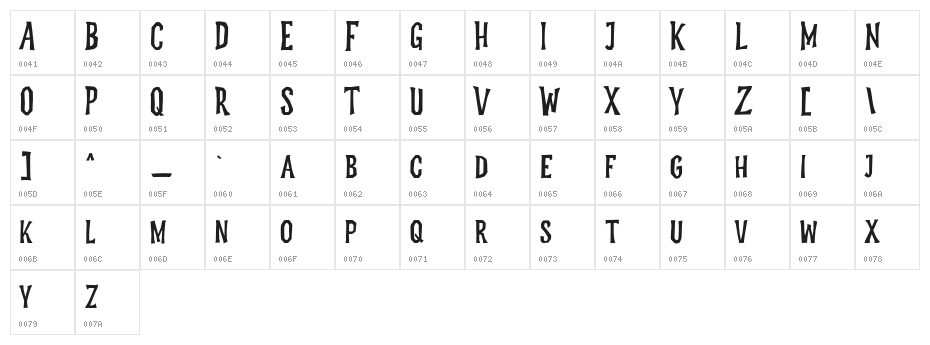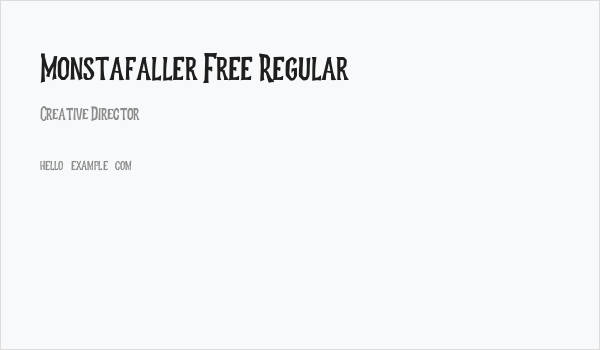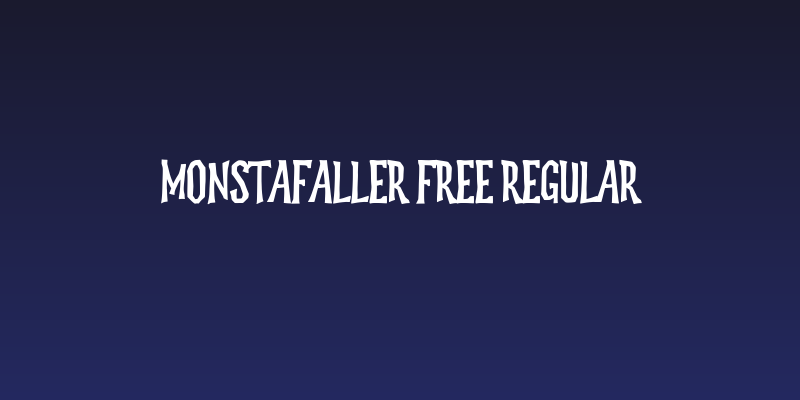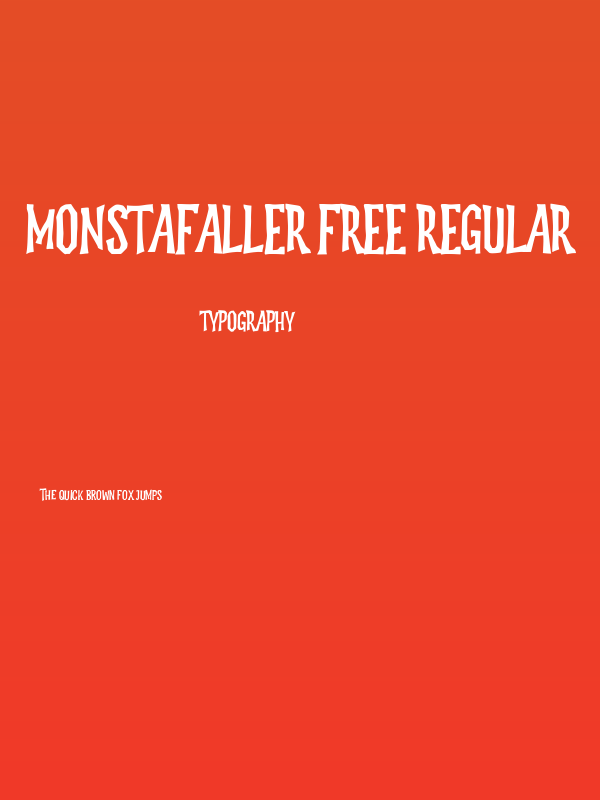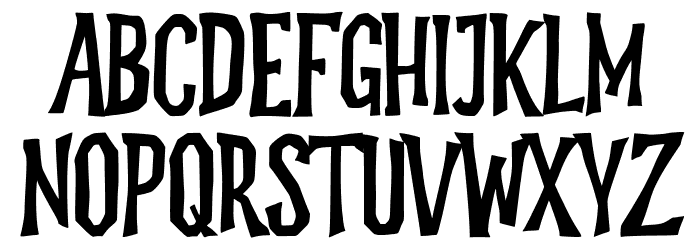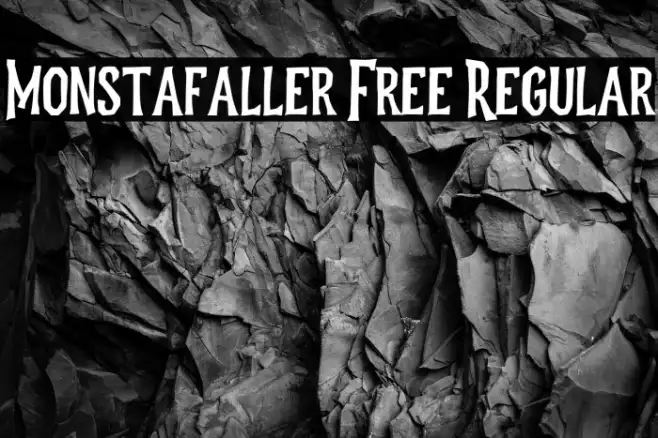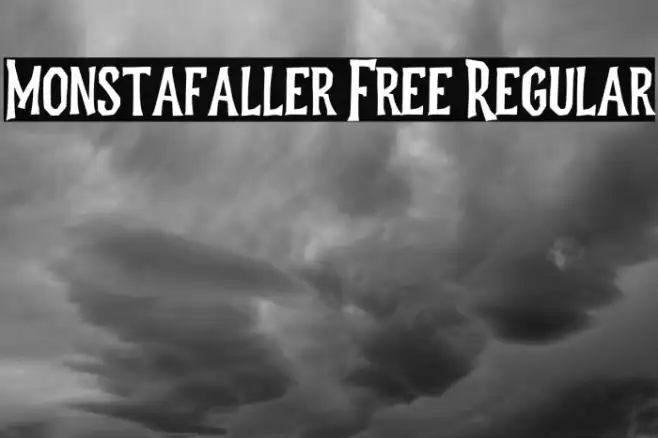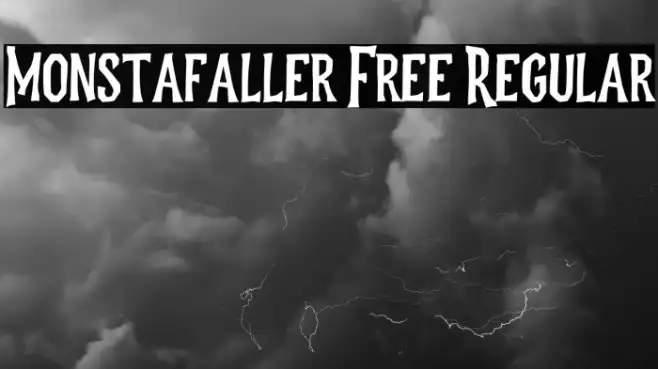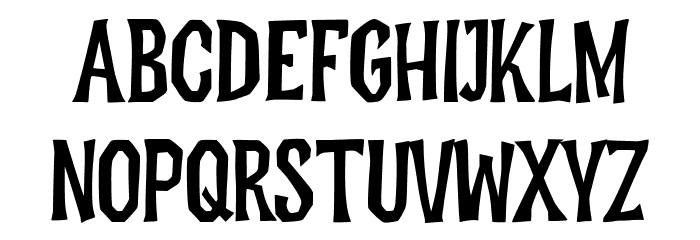
Monstafaller Free Regular Font
| Estilo general | Playful, Energetic, Hand-drawn |
| Proyectos propuestos | Ideal for posters, event flyers, children's book covers, and other playful designs. |